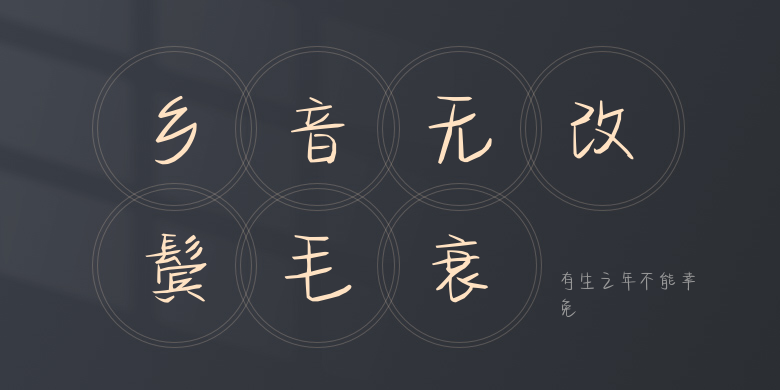
有生之年不能幸免
有生之年不能幸免,这款字体结构工整、笔画清晰,兼顾美观与易读性,适用于标题、正文、海报、包装、LOGO 等多种场景。字形优雅稳定,风格百搭耐看,适配日常排版与创意设计,让文字呈现更舒适、更具质感。有生之年不能幸免一笔一画,皆是细节,以均衡的比例、流畅的线条打造舒适视觉体验,字形端正大气,风格简约现代。无论是商业设计、品牌宣传还是日常排版,都能轻松驾驭,让文字更有格调与力量。有生之年不能幸免字体下载。